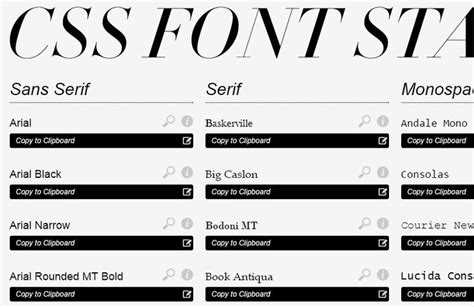
Тег <font> применялся в ранних версиях HTML для изменения шрифта, его размера и цвета прямо в коде. С его помощью веб-разработчики задавали оформление текста без подключения таблиц стилей. Однако с выходом стандарта HTML5 элемент был объявлен устаревшим и больше не поддерживается современными спецификациями.
Основными атрибутами <font> были color, face и size. Атрибут color задавал цвет текста в виде названия (например, «red») или шестнадцатеричного кода (#FF0000). Атрибут face указывал конкретный шрифт, например «Arial» или «Times New Roman». Атрибут size регулировал относительный или абсолютный размер текста от 1 до 7.
Сегодня использование <font> не рекомендуется. Для оформления текста применяются CSS-свойства: color, font-family, font-size. Такой подход обеспечивает гибкость, удобство поддержки и совместимость с любыми браузерами. Тем не менее, знание принципа работы устаревшего тега полезно при поддержке старого кода и корректной его замене современными средствами.
История появления тега font и его роль в раннем HTML
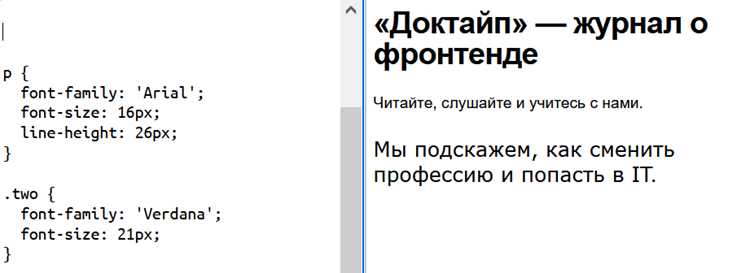
Тег <font> был добавлен в спецификацию HTML 3.2 в 1997 году и предназначался для управления внешним видом текста без применения каскадных таблиц стилей. С его помощью разработчики задавали цвет через атрибут color, размер с помощью size и гарнитуру через face.
В эпоху становления веба <font> фактически заменял стилизацию, обеспечивая возможность визуально выделять элементы текста напрямую в коде. Это позволяло создавать страницы, где заголовки, ссылки и абзацы отличались по цвету и шрифту, что делало интерфейсы более выразительными по сравнению с чистым HTML 2.0.
Однако широкое использование тега привело к перегруженности разметки: каждый цвет или шрифт прописывался вручную, а изменения требовали редактирования десятков строк. Именно эта неэффективность стала одной из причин активного продвижения CSS, где оформление отделялось от структуры.
Какие атрибуты поддерживает тег font
Тег <font> устарел, но в старых документах часто встречаются его атрибуты. Они напрямую влияют на отображение текста без подключения CSS.
- color – задаёт цвет текста. Поддерживаются названия цветов (
red,blue) и шестнадцатеричные значения (#ff0000). - size – определяет размер шрифта. Принимает значения от 1 до 7, где 3 считается стандартным. Возможны относительные значения:
+1,-2. - face – указывает семейство шрифтов. Можно перечислить несколько через запятую, например
Arial, Verdana, sans-serif.
Если используется несколько атрибутов одновременно, они применяются в комплексе. При отсутствии шрифта, указанного в face, браузер подбирает ближайший доступный.
Современная альтернатива – CSS-свойства color, font-size, font-family, которые полностью заменяют функционал <font>.
Как изменить цвет текста с помощью атрибута color
Тег поддерживает атрибут color, который задаёт цвет символов. Значение можно указать в виде названия цвета на английском языке, например <font color="red">Текст</font>, либо в шестнадцатеричном формате, например <font color="#00FF00">Текст</font>.
Браузеры также принимают запись в формате RGB: <font color="rgb(0,0,255)">Текст</font>. Это позволяет гибко управлять оттенками, комбинируя значения от 0 до 255 для каждого канала.
Следует учитывать, что тег и атрибут color считаются устаревшими. Для современного оформления рекомендуется использовать CSS-свойство color, но при изучении старого HTML знание применения атрибута остаётся полезным.
Задание размера шрифта через атрибут size
Атрибут size в теге <font> позволяет изменять размер текста в пределах значений от 1 до 7. По умолчанию используется уровень 3.
Например: <font size=»5″>Текст</font> отобразит шрифт больше стандартного. Минимальное значение 1 делает текст самым мелким, а максимальное 7 – самым крупным.
Кроме абсолютных чисел можно применять относительные значения с префиксом + или —. Запись <font size=»+2″> увеличивает размер относительно базового, а <font size=»-1″> уменьшает его.
Важно учитывать, что интерпретация размеров зависит от браузера. В разных системах результат может визуально отличаться.
Рекомендовано использовать CSS для контроля шрифтов, однако при работе со старыми документами атрибут size остаётся полезным для точной настройки отображения.
Использование атрибута face для выбора гарнитуры
Атрибут face в теге <font> задаёт конкретное название шрифта, который должен отобразиться у пользователя. Указывается одно или несколько значений через запятую, что позволяет браузеру выбрать доступный вариант в системе.
Пример: <font face="Arial, Verdana, sans-serif">Текст</font> – сначала будет использован Arial, при его отсутствии Verdana, и если ни один из них не найден, система применит ближайший шрифт семейства sans-serif.
| Значение face | Особенности отображения |
|---|---|
| Times New Roman | Стандартный шрифт с засечками, присутствует на большинстве устройств |
| Arial | Без засечек, используется как универсальный вариант для веба |
Как заменить тег современными методами?
Заменить можно с помощью CSS, применяя свойства color, font-family и font-size. Например, вместо Текст можно написать <span style=»color:red; font-size:18px;»>Текст</span>. Такой подход позволяет изменять стиль через внешние таблицы стилей, улучшает читаемость кода и упрощает его поддержку, особенно если оформление текста требуется на нескольких страницах.